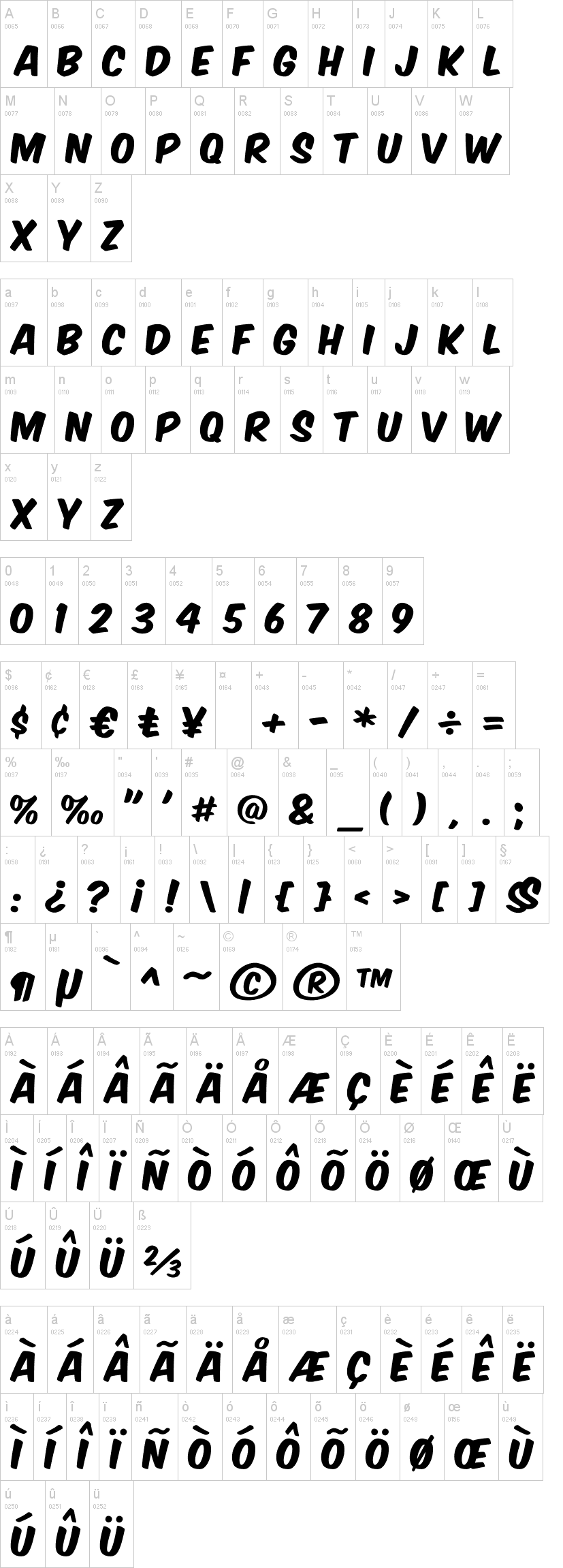
Komika Axis
? Komika Axis 是一款由 Fontry 出品的流行字体,它采用经典的漫画风格,拥有清晰的线条,精细的细节,以及有趣的字形。它的特点在于其独特的视觉效果,可以让文本看起来更加精致,有趣,而且非常容易读取。它可以用于各种漫画,游戏,广告,网页和其他印刷品的设计,可以为您的项目增添时尚的外观。
Komika Axis是一款非常不错的手写艺术字体,具有很好的视觉感,适合于文化类的宣传设计、商业类品牌的广告和产品包装设计以及个性化文字排版等较多场景。
Komika Axis字符映射图